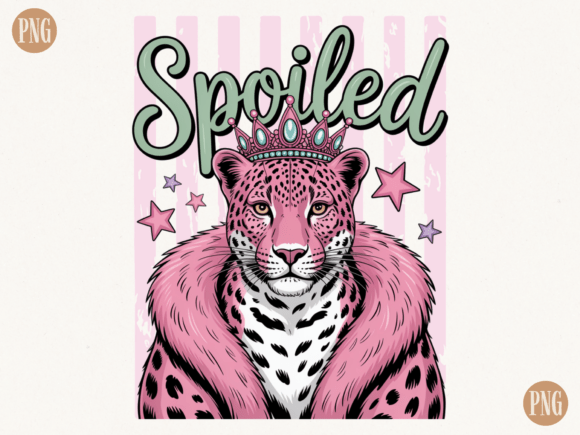
Spoiled Leopard – Trendy Pink Coquette a
Conçu avec précision, Spoiled Leopard – Trendy Pink Coquette a offre des vecteurs nets, une typographie fluide et une licence commerciale pour une tranquillité d'esprit.